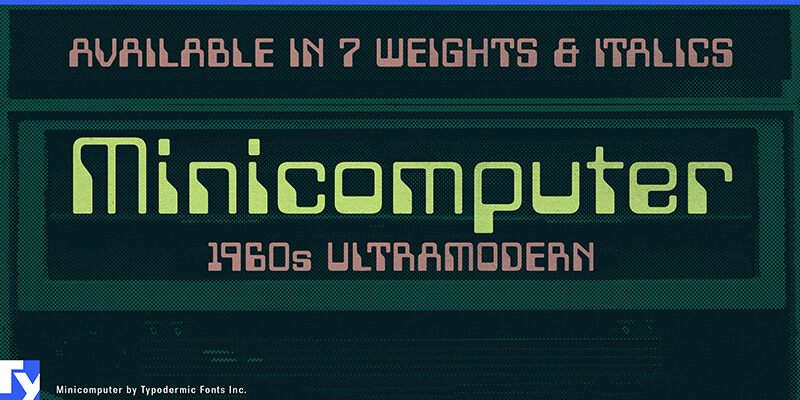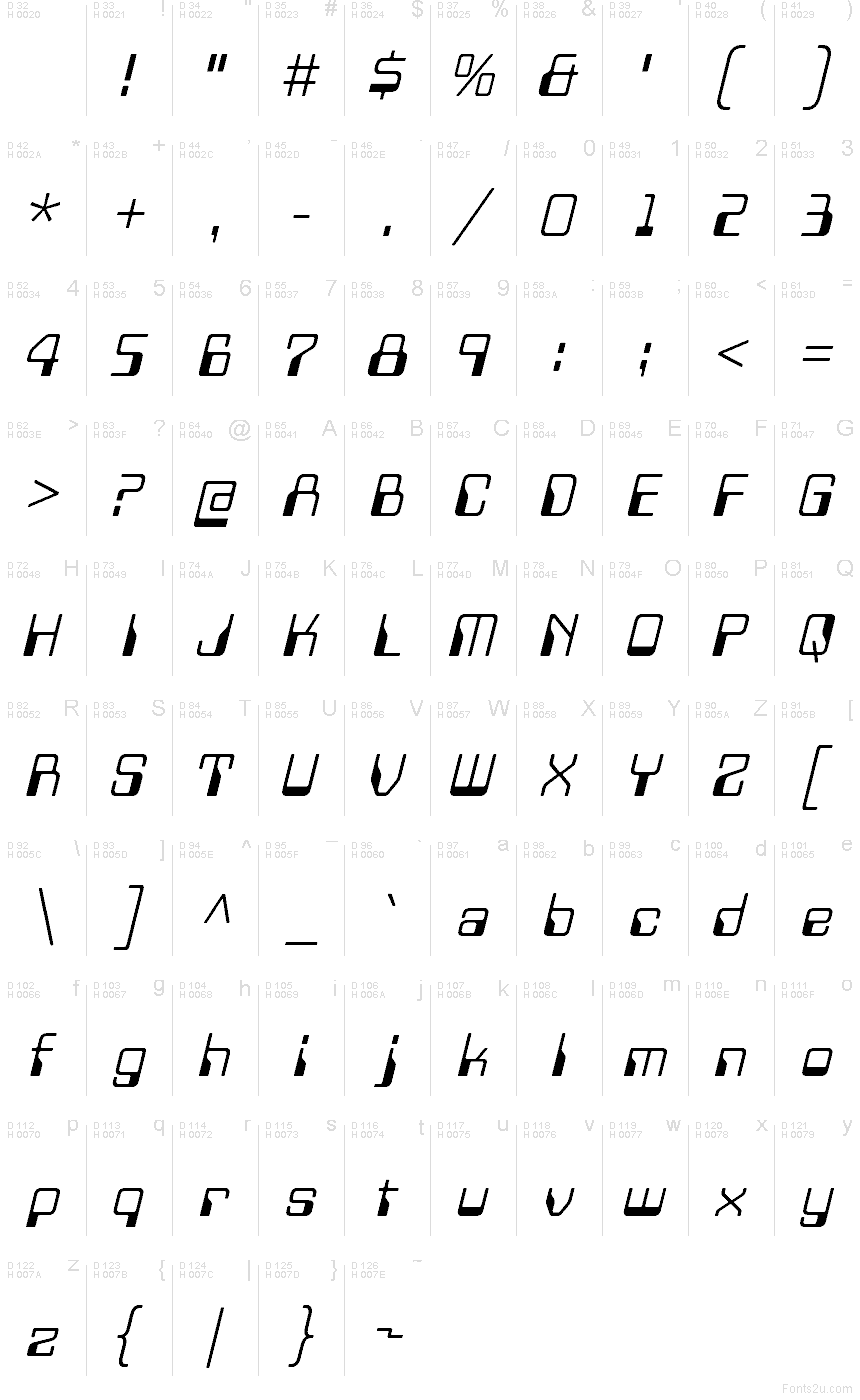
Minicomputer je display písmo inspirované znaky MICR E-13B, které se kdysi tiskly na bankovní šeky. Spojuje výpočetní preciznost poloviny 20. století s hravým duchem retrofuturismu 60. let a proměňuje ryze funkční styl v něco expresivního a stylového.
Hranaté tvary a charakteristické číslice odkazují na displeje dobových strojů, zatímco kompletní abeceda rozšiřuje tento styl do titulků, brandingu, plakátů i redakčního designu. Díky široké jazykové podpoře a čistému geometrickému rytmu přináší Minicomputer do moderní typografie nádech retro techniky.